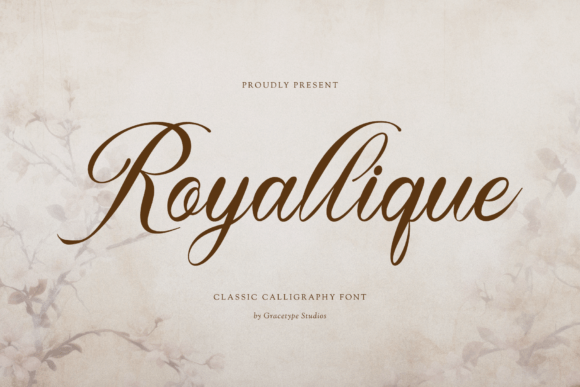
Royallique
Việc tìm kiếm các thành phần thiết kế phù hợp có thể là một thách thức, nhưng Royallique cung cấp một bộ sưu tập đặc biệt giúp nâng tầm công việc của bạn ngay lập tức.
Được chế tác với độ chính xác cao, Royallique cung cấp các vector sạch, kiểu chữ mượt mà và giấy phép thương mại để bạn yên tâm.
Cho dù bạn đang tạo sản phẩm POD (In theo yêu cầu), thiệp mời đám cưới hay đồ họa mạng xã hội, Royallique đều là một sự lựa chọn lý tưởng.